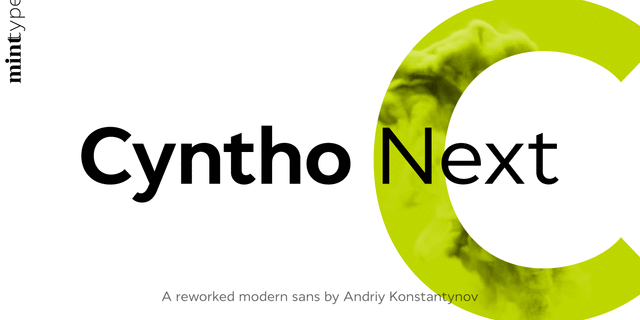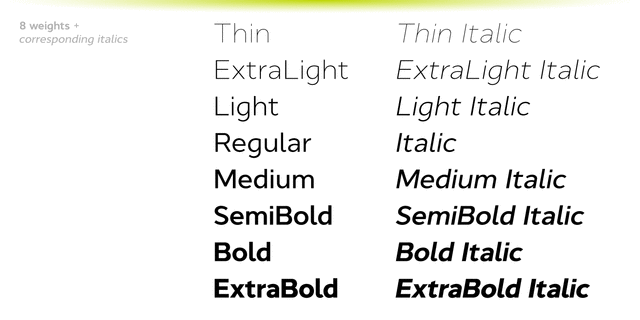
Cyntho Next – это современный геометрический шрифт без засечек, в основе которого гибридная каплевидная контрформа. Имеет 8 начертаний от тонкого до сверхжирного, включая кириллицу, а также богатые функции OpenType.
Cyntho Next был полностью переделан на основе нашего бестселлера Cyntho Pro. Так же есть аналогичный брусковый шрифт – Cyntho Next Slab.
Шрифт разработал Андрей Константинов в 2019 году.
Ассоциации c начертанием Cyntho Next Semi Bold ItalicКачества и характер:
простой, твердый, ровный, точный, понятный, доступный, элементарный, правильный, лаконичный, минималистичный, городской, строгий, серьезный, устойчивый, статичный, стабильный, качественный, четкий, самостоятельный, ответственный, западный, деловой, логичный, холодный, спокойный, современный, модный, обязательный, сильный, убедительный, урбанистический, надежный, глобализированный, глобалистичный, чертежный, инженерный, чистый, нейтральный, умеренный, стандартный, невыразительный, универсальный, умный, популярный, урбанистичный
общество, город, транспорт, аэропорт, метро, навигация, лекарство, инновации, архитектура, наука, дизайн, бизнес, торговля, реклама, магазин, конструктор, чертеж, техника, прибор, урбанистика, деньги, банкнота, медицина, зубная паста, новости, автобус, технологии, инженер, коворкинг, образование, математика, монета, химия, физика Стилистика: